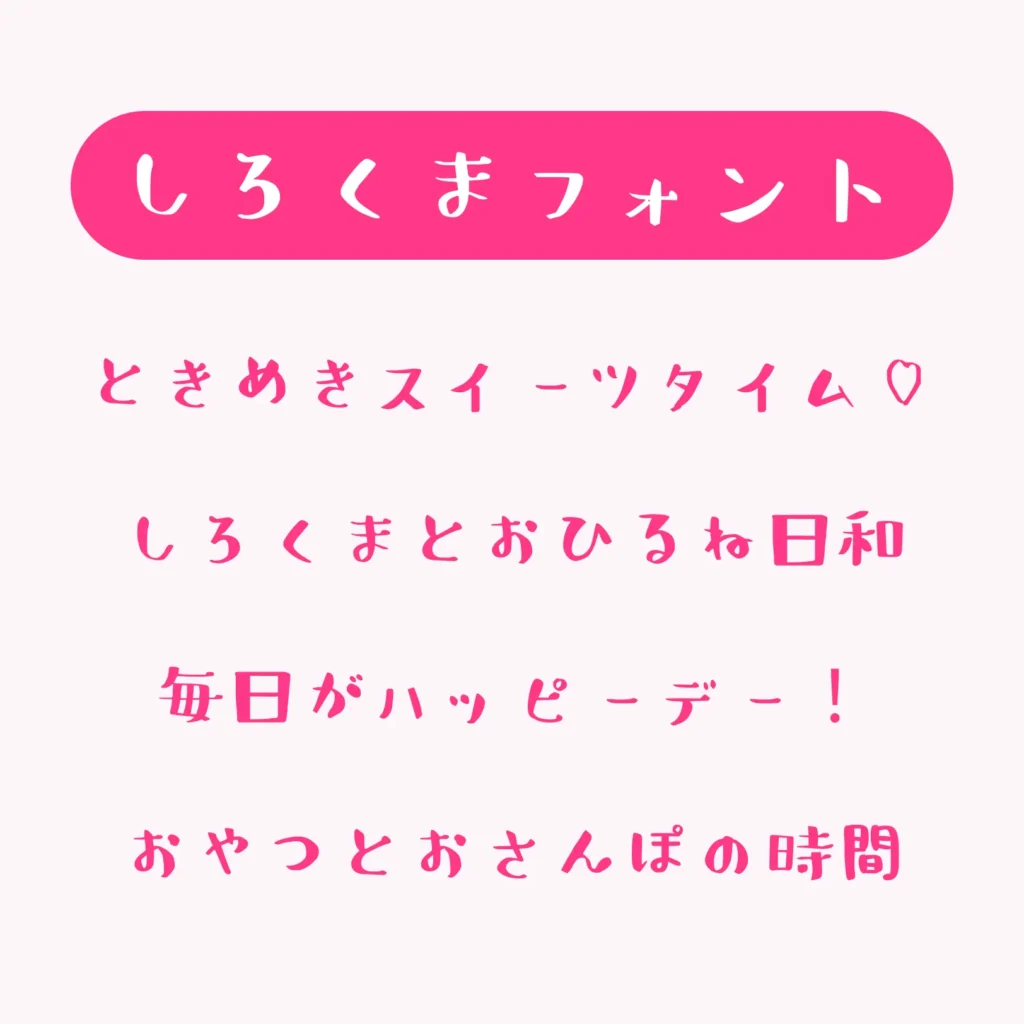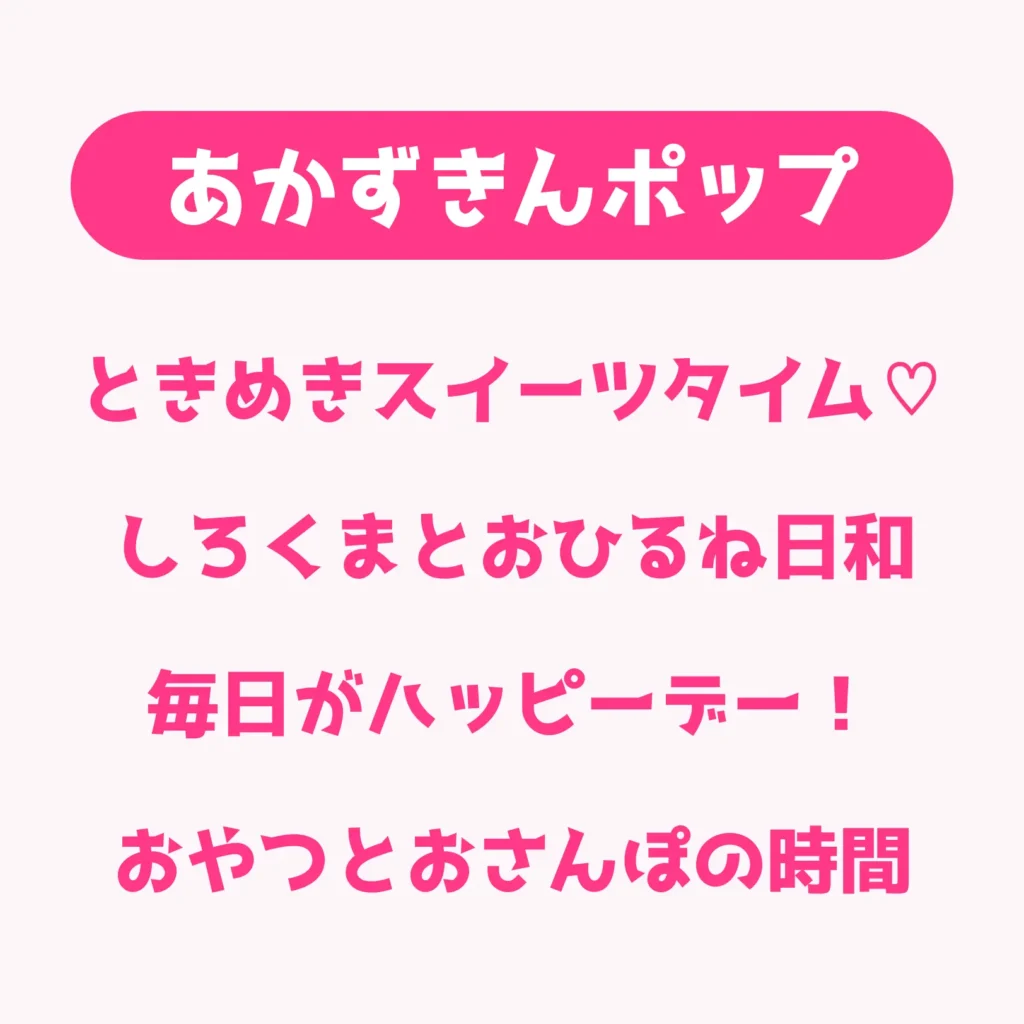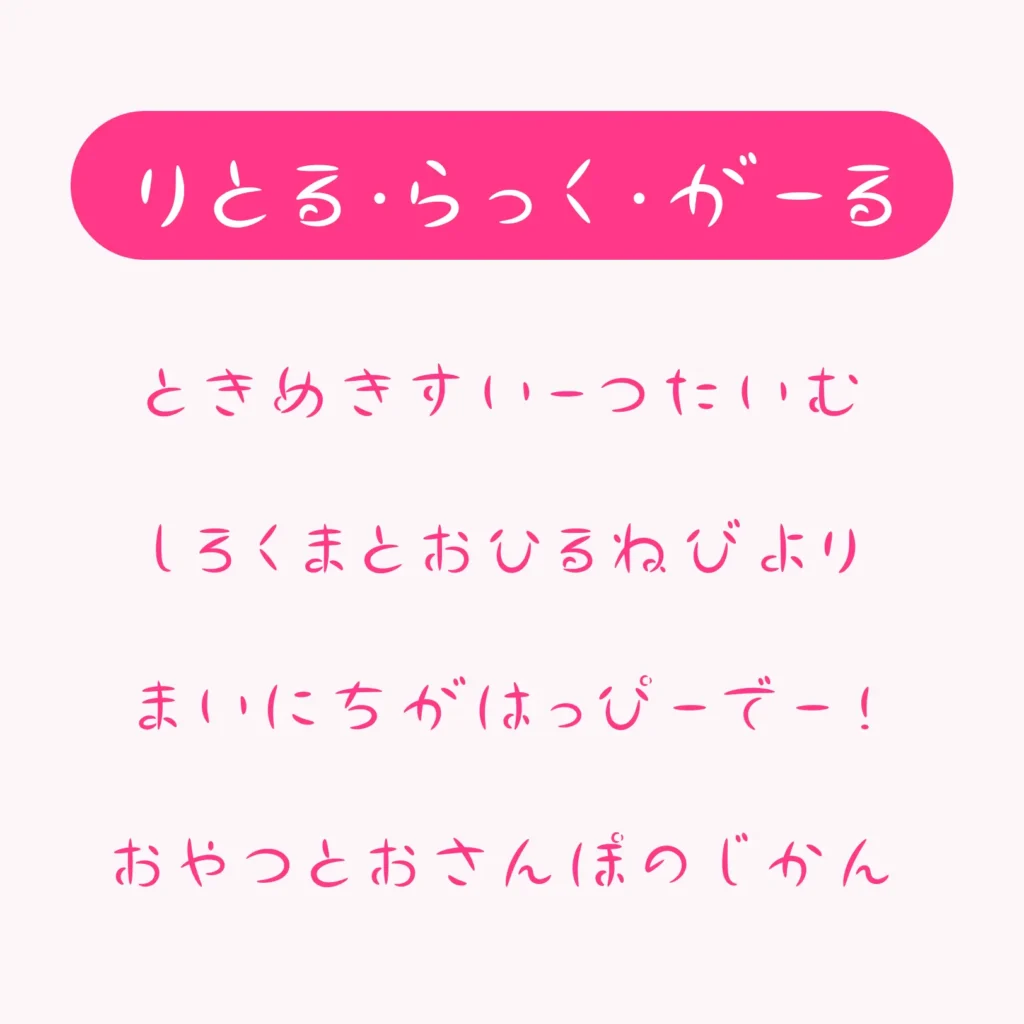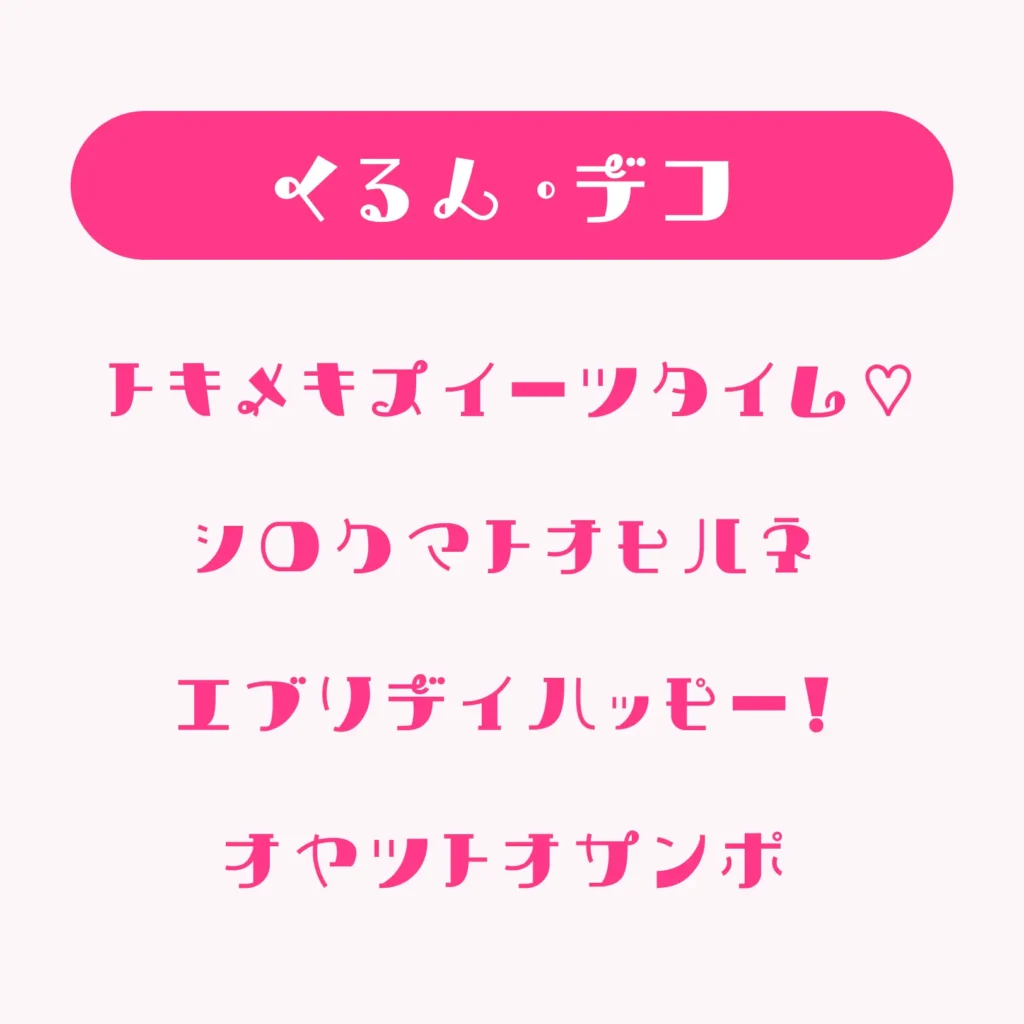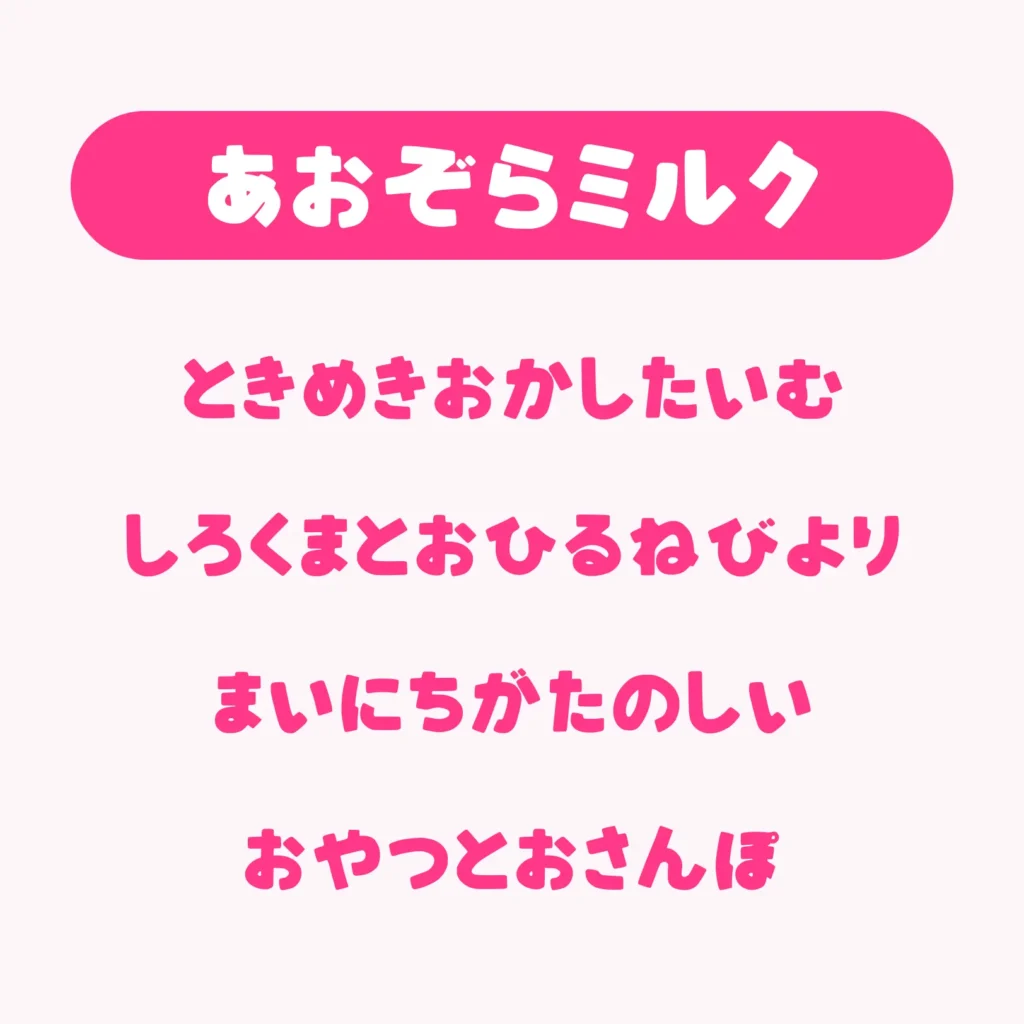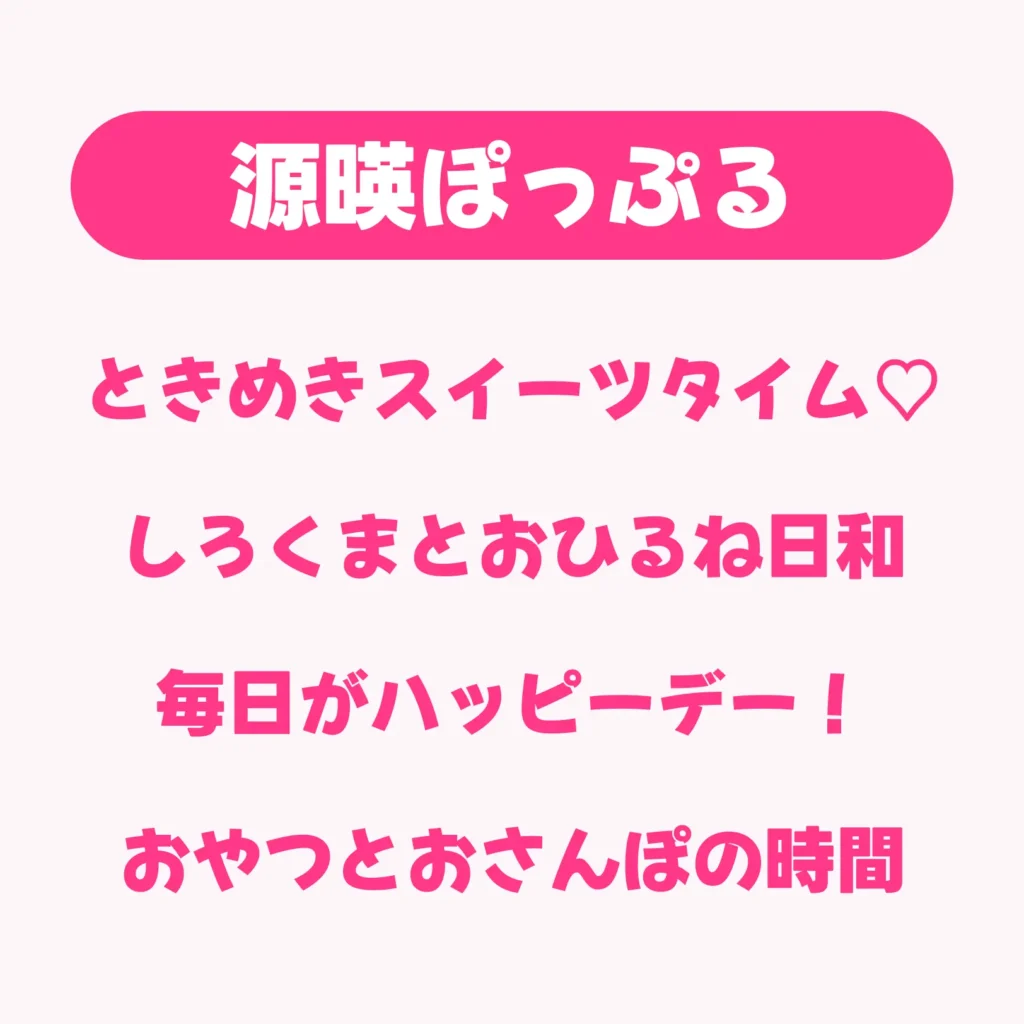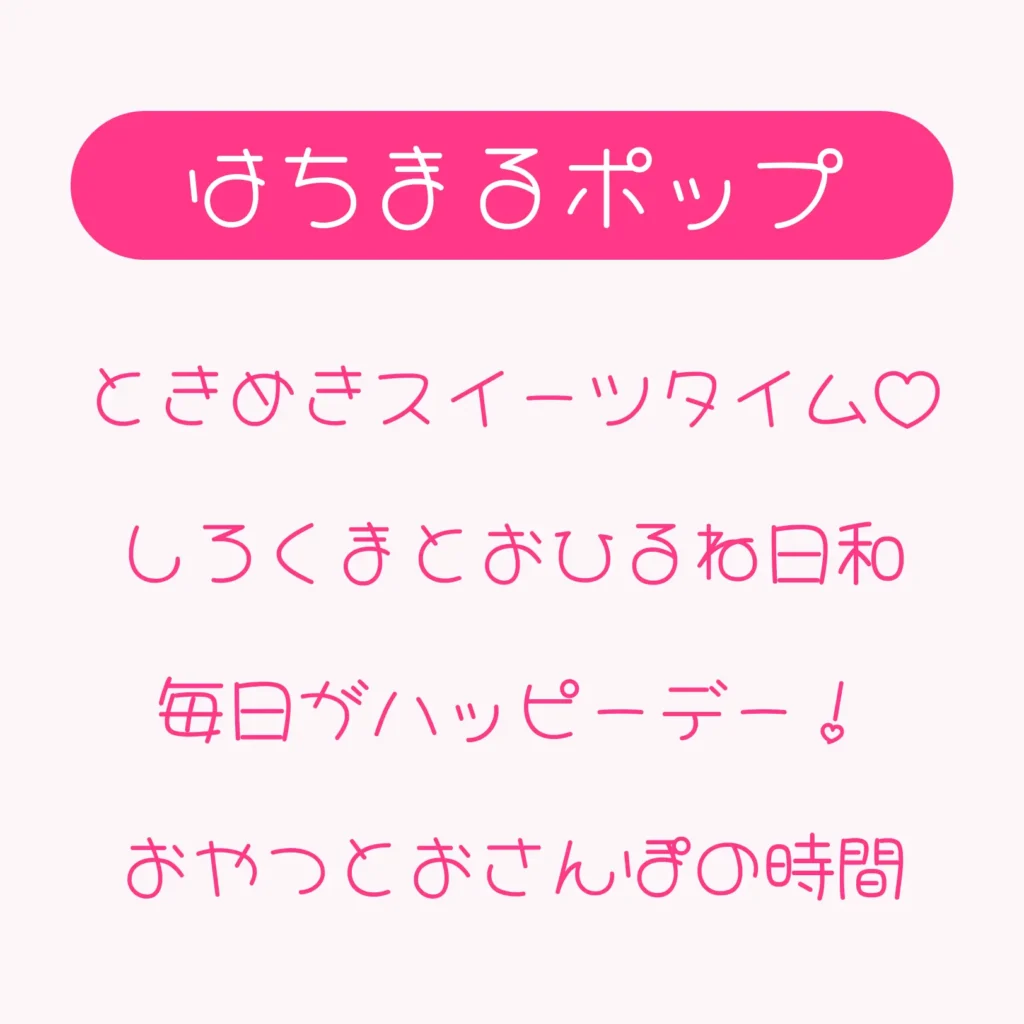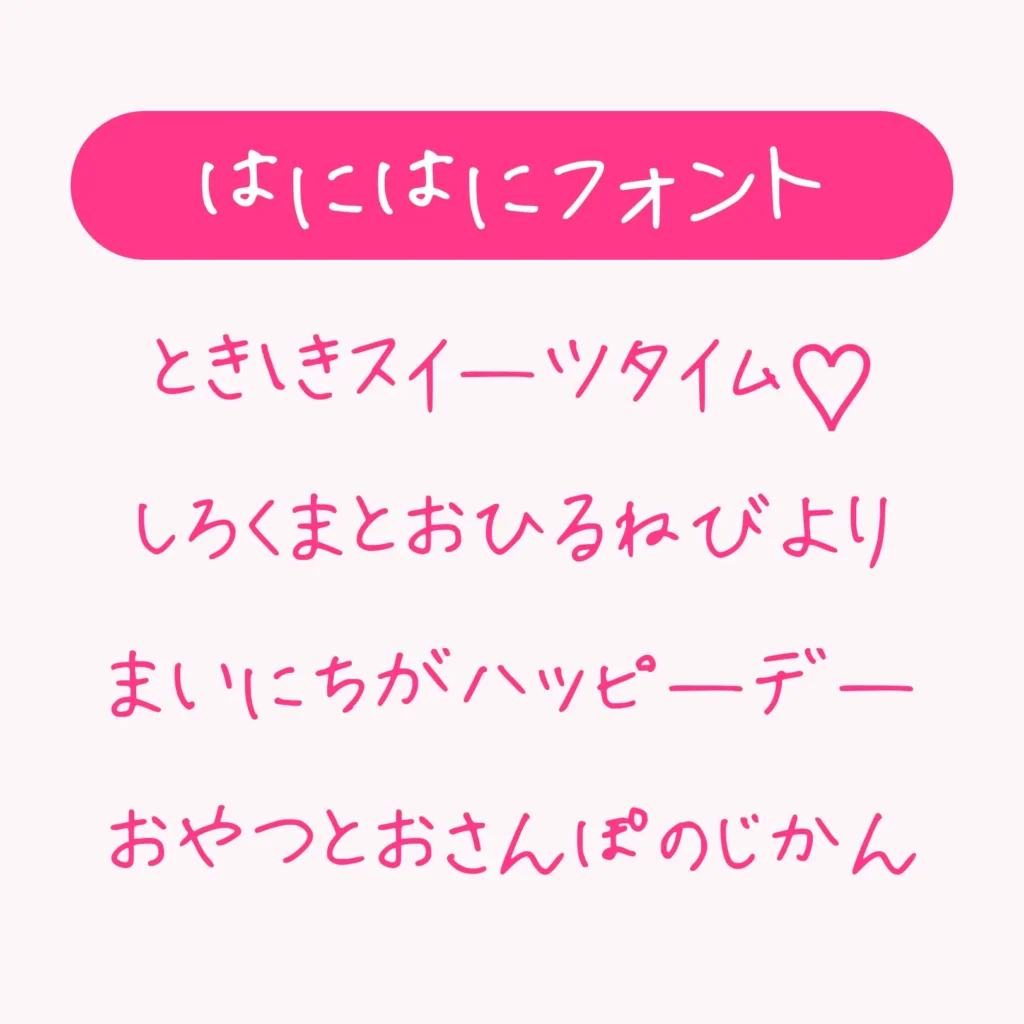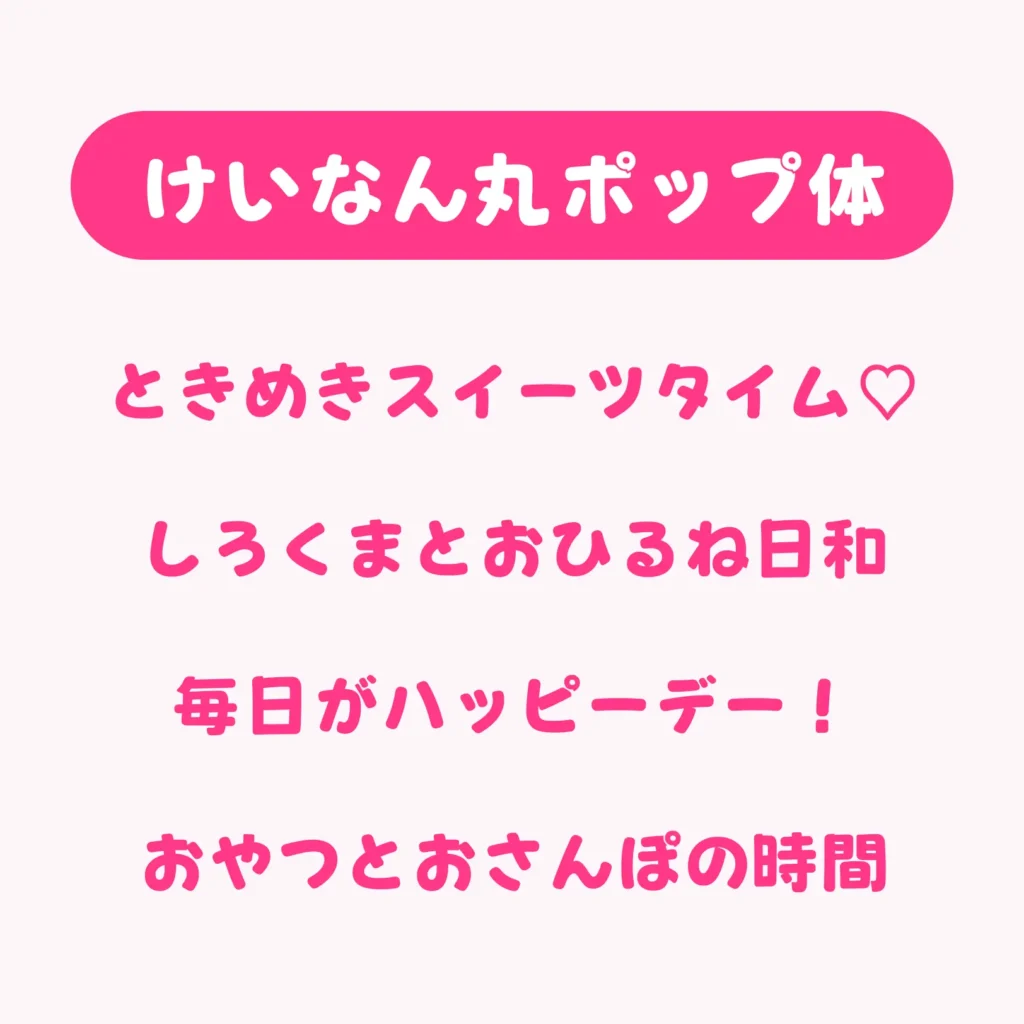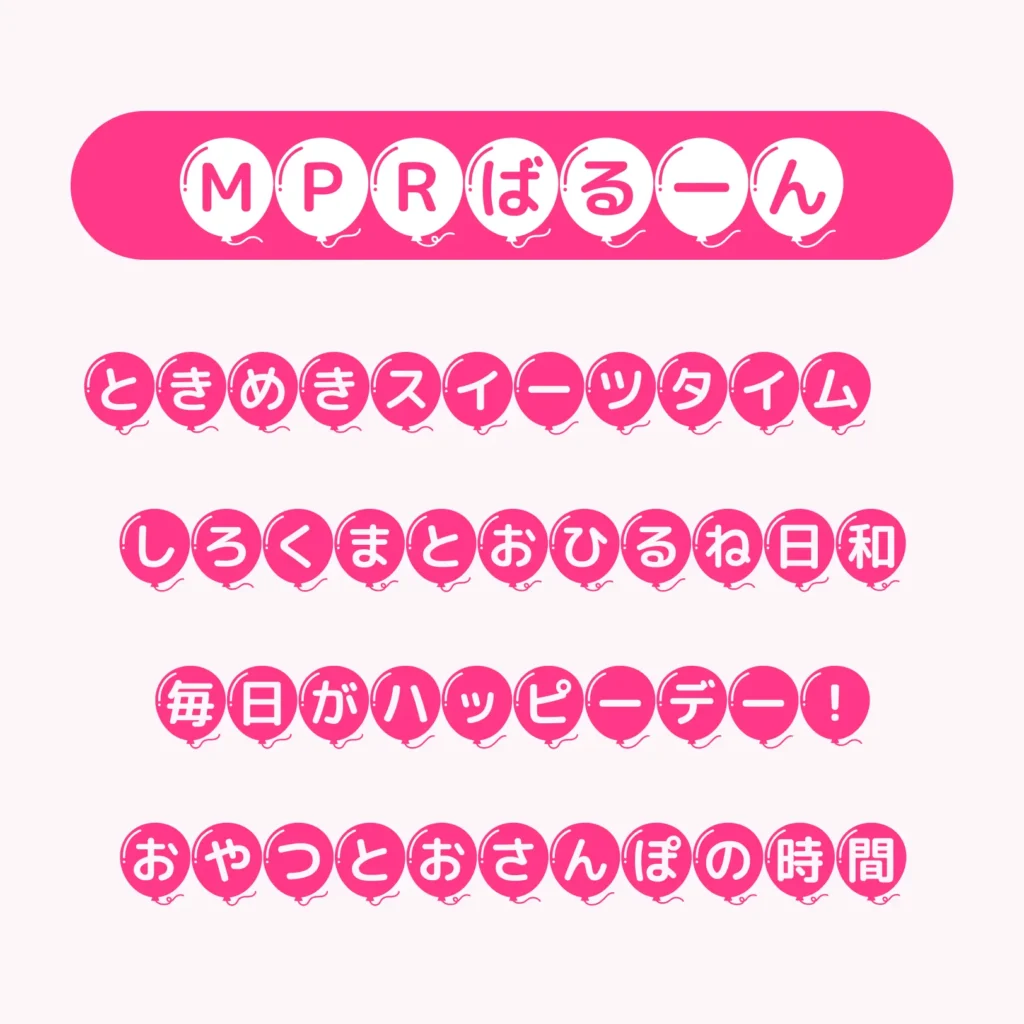
かわいいフォントおすすめ30選|商用利用OKの無料フリーフォントまとめ
かわいいフリーフォント30選
「かわいい」フリーフォントをご紹介!
丸みのあるやさしいラインが特徴のかわいい系フリーフォントは、ガーリーやポップ、ナチュラルなど様々なテイストのデザインに活躍します。
かわいいいフォント
無料で使えて商用利用もできるかわいいフォントを集めました。丸みのある文字やポップなデザイン、手書き風など、可愛さのテイストもさまざま。どんなシーンで使うと映えるのかも、あわせてご紹介します。
デザインの雰囲気づくりや、用途にぴったりのフォント探しのヒントとして、ぜひ参考にしてみてください。
かわいい文字一覧
1. めおめおフォント
めおめおフォント
収録文字ひらがな・カタカナ・英字・数字・記号
活用シーン例ショップカード/SNS投稿/やさしい印象のロゴ
柔らかな丸みと素朴でやさしい線が魅力のフォントです。手書きのような温かみがあり、ガーリーなデザインや、ゆるく親しみやすい雰囲気を出したいときにぴったり。ロゴやSNS画像、カードデザインなど幅広く使えます。
2. ふてほど丸ゴシック
ふてほど丸ゴシック
収録文字漢字・ひらがな・カタカナ・英字・数字・記号
活用シーン例ポスター/イベントタイトル/バナー広告
しっかりとした太めのラインに丸みを加えた、可愛らしくも存在感のあるフォントです。見やすさと柔らかさを兼ね備えているので、イベントタイトルや見出しなど目立たせたい場面におすすめ。
3. けいなん丸ポップ体
けいなん丸ポップ体
収録文字漢字・ひらがな・カタカナ・英字・数字・記号
活用シーン例子ども向けチラシ/POP/カジュアルなロゴ
ころんと弾むような形が印象的な、元気で明るい雰囲気のフォントです。親しみやすくカジュアルなデザインに合わせやすく、POPや子ども向けの制作物にもぴったり。
4. 源暎ぽっぷる
源暎ぽっぷる
収録文字漢字・ひらがな・カタカナ・英字・数字・記号
活用シーン例SNS画像/ゲーム・アニメ系デザイン/若者向け広告
元気で明るい印象を与える、カジュアルで使いやすい丸ゴシック体です。シンプルながらも程よい可愛さがあり、幅広いジャンルのデザインに活用できます。
5.にくまる
にくまる
収録文字漢字・ひらがな・カタカナ・英字・数字・記号
活用シーン例お菓子パッケージ/雑貨ロゴ/やわらかい雰囲気のチラシ
ふっくらとした厚みのある文字が特徴の、温かみのあるフォントです。やさしい雰囲気を演出したいときや、ほのぼのとしたデザインにおすすめです。
6. さなフォン丸
さなフォン丸
収録文字漢字・ひらがな・カタカナ・英字・数字・記号
活用シーン例カフェメニュー/コスメ販促/ショップロゴ
手書き感のあるやさしいタッチと、丸ゴシックの安定感を合わせたフォントです。ナチュラルで柔らかな印象を与え、女性向けや落ち着いたデザインにもマッチします。
7. メロディライン
メロディライン
収録文字カタカナ・記号
活用シーン例音楽イベントポスター/ライブ告知/カジュアルロゴ
軽やかでリズム感のある線が印象的なフォントです。楽しさや動きを感じさせるデザインにぴったりで、音楽関連やイベント告知におすすめ。
8. そし太マル
そし太マル
収録文字ひらがな・カタカナ・英字・数字・記号
活用シーン例イベント見出し/ポップ広告/屋外ポスター
がっしりとした太さと丸みのあるフォルムで、視認性抜群の書体。タイトルロゴや見出しに使うと存在感があり、ポップ系からキッズ向けまで幅広く使える万能さが魅力です。
9. MPRばるーん
MPRばるーん
収録文字漢字・ひらがな・カタカナ・英字・数字・記号
活用シーン例子ども向けイベント/バースデーカード/パーティ案内
風船のようにぷっくりとした形状が特徴で、見た瞬間に楽しい気分になるフォント。キッズイベントやお祭りポスター、パーティの案内など、明るくポップな場面でおすすめです。
10. あこがれのまるもじ
あこがれのまるもじ
収録文字ひらがな・カタカナ・英字・数字・記号
活用シーン例店頭POP/雑誌見出し/商品タグ
クセがなく、素直で親しみやすい形の丸文字です。幅広いジャンルで使いやすく、普段使いのデザインにも自然になじみます。
11. Weekend Citron
Weekend Citron
収録文字英字・数字
活用シーン例カフェメニュー/SNS用画像/季節イベント案内
軽やかで爽やかな手書き感が魅力のフォントです。ラフすぎず上品さもあり、ナチュラルでおしゃれなデザインにぴったり。
12.ネコミミフォント
ネコミミフォント
収録文字カタカナ・英字・数字
活用シーン例動物イベント/キャラクターグッズ/ユニークロゴ
文字の一部に猫耳モチーフがあしらわれた、遊び心あふれるフォントです。ペットショップや動物関連イベント、キャラクター商品などにぴったりで、見た人をクスッと笑顔にします。
13.くちばしフォント
くちばしフォント
収録文字ひらがな・カタカナ・数字
活用シーン例インパクトロゴ/イベントタイトル/アート系フライヤー
端がくちばしのように尖ったユニークな形のフォントです。個性を強調したいタイトルやアート寄りのデザインにおすすめ。
14.りとる・らっく・がーる
りとる・らっく・がーる
収録文字ひらがな・カタカナ・英字・数字
活用シーン例雑貨パッケージ/女性向けロゴ/招待状
やわらかくガーリーな雰囲気が漂う手書き風フォントです。可愛らしい世界観づくりにぴったりで、女性向けデザインにマッチします。雑貨、コスメのパッケージなど、やさしい可愛さを演出したいデザインにぴったりです。
15.くるん・デコ
くるん・デコ
収録文字ひらがな・カタカナ・英字・数字
活用シーン例アイドルイベント/スイーツショップロゴ/カラフルチラシ
文字の端にくるんとした装飾が付いた、ファンシーで華やかなフォントです。タイトルや見出しを一気に可愛く彩り、ポップでガーリーな世界観を演出できます。
16.子パンダフォント
子パンダフォント
収録文字カタカナ・数字
活用シーン例キッズパッケージ/園の案内/子ども向けイベント
丸く太めの文字で、まるでぬいぐるみのような愛らしさを持つフォントです。子ども向けコンテンツやキャラクターグッズ、キッズイベントのタイトルにおすすめです。
17.ふんわりラウンド
ふんわりラウンド
収録文字ひらがな・カタカナ・英字・数字・記号
活用シーン例ハンドメイドロゴ/ショップカード/女性向け広告
ソフトな曲線と丸みで優しい印象を与えるフォントです。ナチュラルテイストのショップロゴや、女性向けの広告、手作り感を出したいカードなどにぴったりです。
18.ふんわりうさぎフォント
ふんわりうさぎフォント
収録文字ひらがな・カタカナ
活用シーン例ガーリーブランド/パステルデザイン/雑貨パッケージ
うさぎのような柔らかさと可愛さを感じさせるフォントです。ガーリーな見出しやパステル調のデザインにマッチし、愛らしい雰囲気を演出します。
19.ポプらむ☆キュート
ポプらむ☆キュート